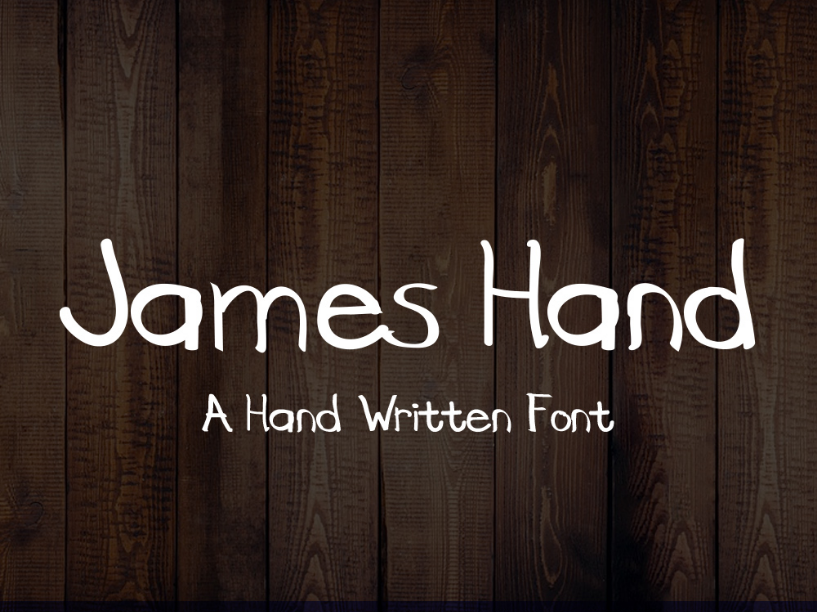
Através do talentoso trabalho do designer Hamilton, apresentamos uma nova opção para seu projeto designístico: a fonte ‘James Hand Font’. Inspirada na mão escrita autêntica de um verdadeiro artista da letra, James Hand é algo que vai deixar sua impressão em qualquer texto. Através do software específico utilizado por Hamilton, o resultado é uma linha suave e perfeitamente polida. Inclui tanto letras maiúsculas quanto minúsculas, assim como números e símbolos comuns e pontuação. Este é um verdadeiro exemplo de criação artística, apresentando uma fonte de escrita manual que traz vida à sua ideia visual. Se você está procurando por algo singular para personalizar as suas mensagens digitais, Hamilton’s ‘James Hand Font’ certamente será a escolha ideal.